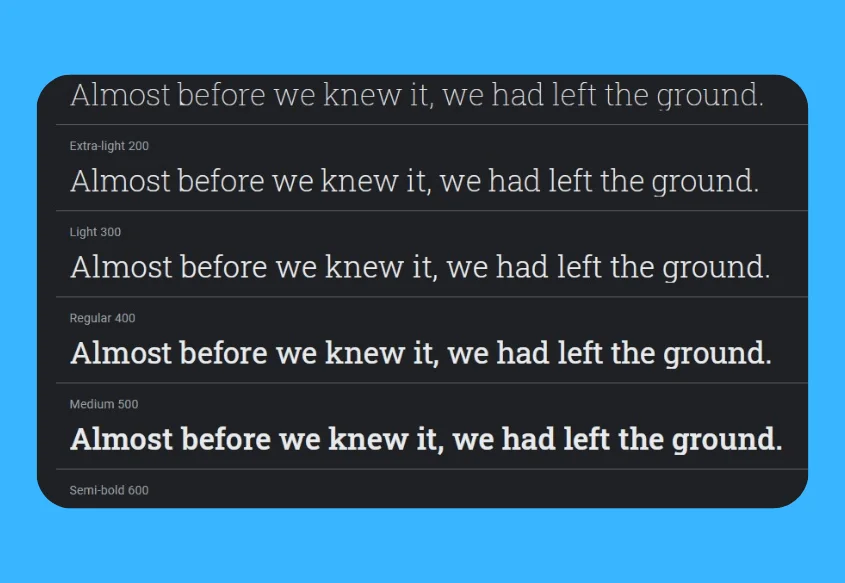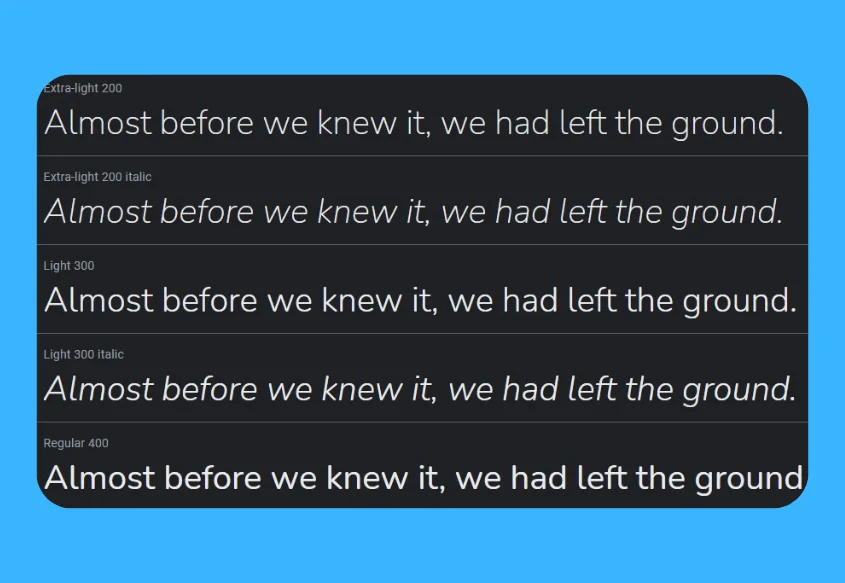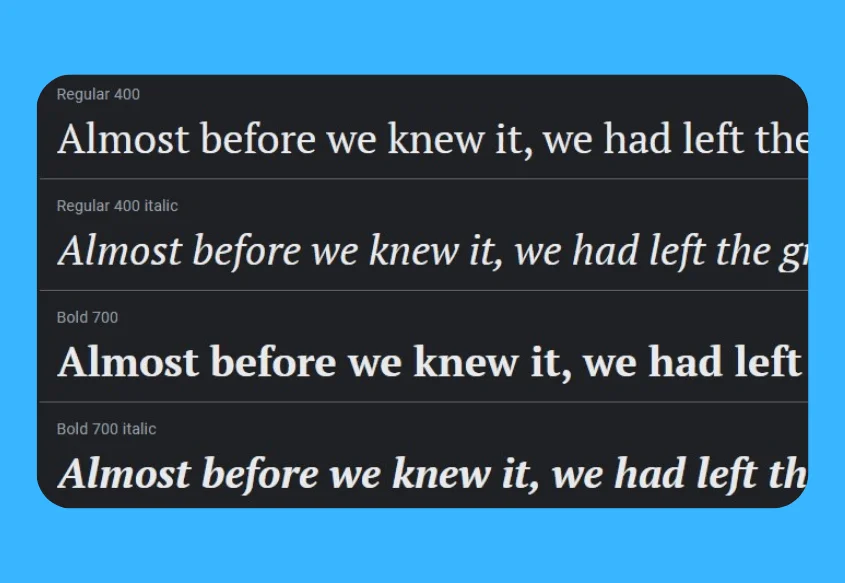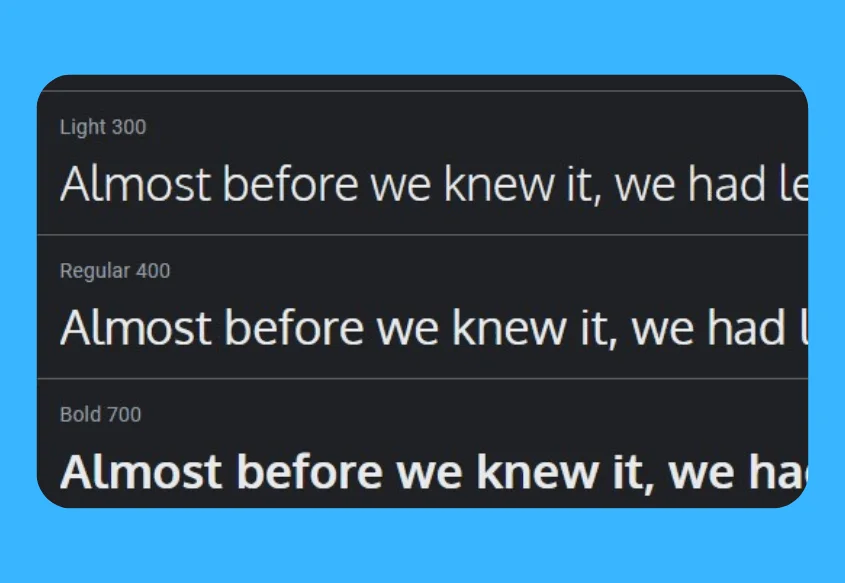
robot
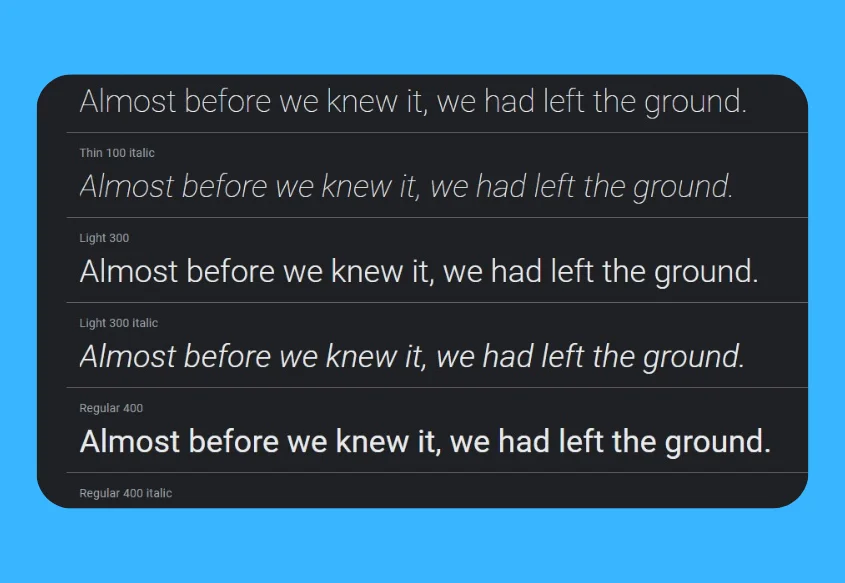
Roboto oleh Christian Robertson bersifat mekanis hingga ke intinya dan sebagian besar memiliki bentuk geometris. Namun demikian, font ini menawarkan kurva yang sangat ramah dan terbuka. Kebanyakan grotesk dikenal karena mendistorsi bentuk huruf mereka dalam upaya yang sia-sia untuk memaksa ritme, Roboto memilih untuk membiarkan huruf-huruf itu menyesuaikan diri dengan lebar alaminya. Inilah sebabnya mengapa font ini menghasilkan ritme membaca yang alami – kualitas yang lebih umum di antara tipe serif dan humanis.
Keluarga regulernya memungkinkan Anda menggunakan Roboto bersama keluarga Roboto Slab dan Roboto Condensed.
Gaya Huruf: Tipis 100, Tipis 100 Italic, Light 300, Light 300 Italic, Regular 400, Regular 400 Italic, Medium 500, Medium 500 Italic, Bold 700, Bold 700 Italic, Black 900, dan Black 900 Italic.
Buka Sans
Open Sans adalah font luhur yang akan terlihat terbaik saat Anda menggunakannya di header dengan opsi variasi semi-tebal. Dengan garis besar yang tajam dan tidak samar, ini sangat mudah dibaca. Anda dapat mencampuradukkannya dengan menggunakannya untuk tajuk Anda dan kemudian menulis deskripsi atau elaborasi menggunakan font lain yang mirip, seperti Helvetica Now. Anda juga dapat mengatur ulang mereka dan menggunakan Open Sans di badan, dan Open Sans yang berani untuk header.
Open Sans adalah jenis huruf sans serif humanis yang luar biasa yang dibuat oleh Type Director Ascender Corp, Steve Matteson. Dia memiliki lebih dari seperempat abad dalam bisnis dan telah merancang wajah untuk Xbox, Android, Microsoft, Citrix, dan Nextel. Versi ini hadir dengan set karakter 897 yang komprehensif, termasuk Latin CE, standar ISO Latin, Cyrillic, dan set karakter Yunani. Open Sans memiliki desain dasar bentuk terbuka, tekanan tegak, dan suasana netral, meskipun ramah. Ini menawarkan pengoptimalan untuk antarmuka seluler, web, dan cetak. Ini juga menawarkan keterbacaan yang luar biasa dalam bentuk hurufnya.
Gaya Huruf: Light 300, Light 300 Italic, Regular 400, Regular 400 Italic, Semi-Bold 600, Semi-Bold 600 Italic, Bold 700, Bold 700 Italic, Extra-Bold 800, dan Extra-Bold 800 Italic.
Poppins
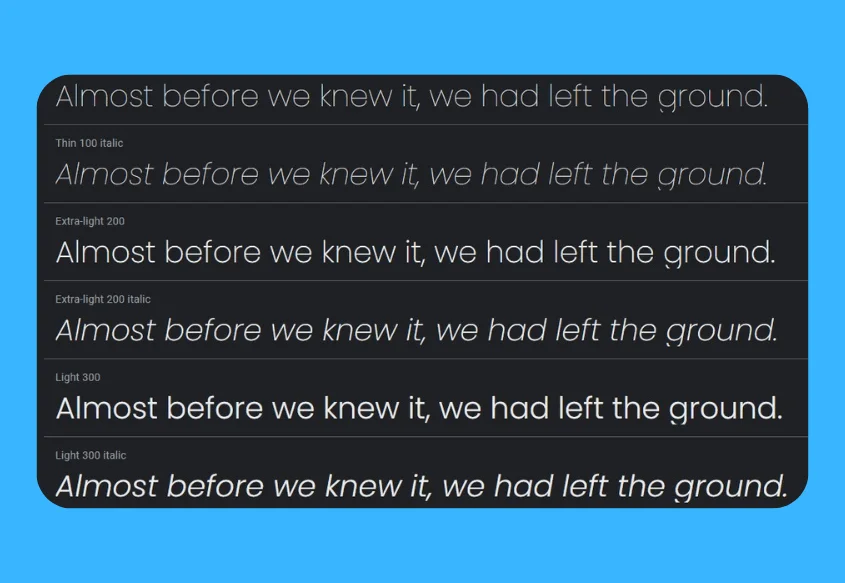
Poppins adalah salah satu jenis huruf sans serif geometris terbaru, yang dibuat oleh Indian Type Foundry dan Jonny Pinhorn. Ini memiliki pendekatan internasionalis untuk genre karena mendukung sistem penulisan Latin dan Devanagari.
Kebanyakan mesin terbang Latin seperti ampersand lebih rasionalis dan dibangun dari biasanya. Desain Devanagari baru, dan ini adalah jenis huruf Devanagari pertama yang memiliki berbagai bobot dalam genre. Baik sistem penulisan Latin dan Devanagari didasarkan pada geometri murni sambil berfokus pada lingkaran.
Setiap bentuk huruf hampir monolinear, dengan sambungan guratannya menampilkan koreksi optik, yang penting untuk mempertahankan warna tipografi yang seragam. Tinggi ascender Latin dan tinggi karakter dasar Devanagari sama; karakter Devanagari lebih tinggi dari huruf kapital Latin. Tinggi x Latin diatur cukup tinggi.
Gaya Huruf: Tipis 100, Tipis 100 Italic, Extra-Light 200, Extra-Light 200 Italic, Light 300, Light 300 Italic, Regular 400, Regular 400 Italic, Medium 500, Medium 500 Italic, Semi-Bold 600, Semi-Bold 600 Miring, Tebal 700, Tebal 700 Miring, Ekstra Tebal 800, Ekstra Tebal 800 Miring, Hitam 900, dan Hitam 900 Miring.
Pasangan Font: Open Sans, Roboto, Source Sans Pro, Roboto Slab, dan Lato.
Noto Sans JP
Noto adalah keluarga Sans Jepang. Ini adalah salah satu dari sedikit keluarga font yang mencoba mendukung semua bahasa di dunia. Noto menawarkan gaya Light, Thin, Demi Light, Medium, Regular, Bold, dan Black.
Noto Sans JP dibuat oleh Google Principal Design. Ini disubset ke semua kanji di JIS X 0213, JIS X 0212, dan JIS X 0208, termasuk semua kanji dalam Adobe-Japan 1-6. Karena browser telah menangani bobot non-X00, bobot Demi Light dari Noto Sans JP telah dihapus.